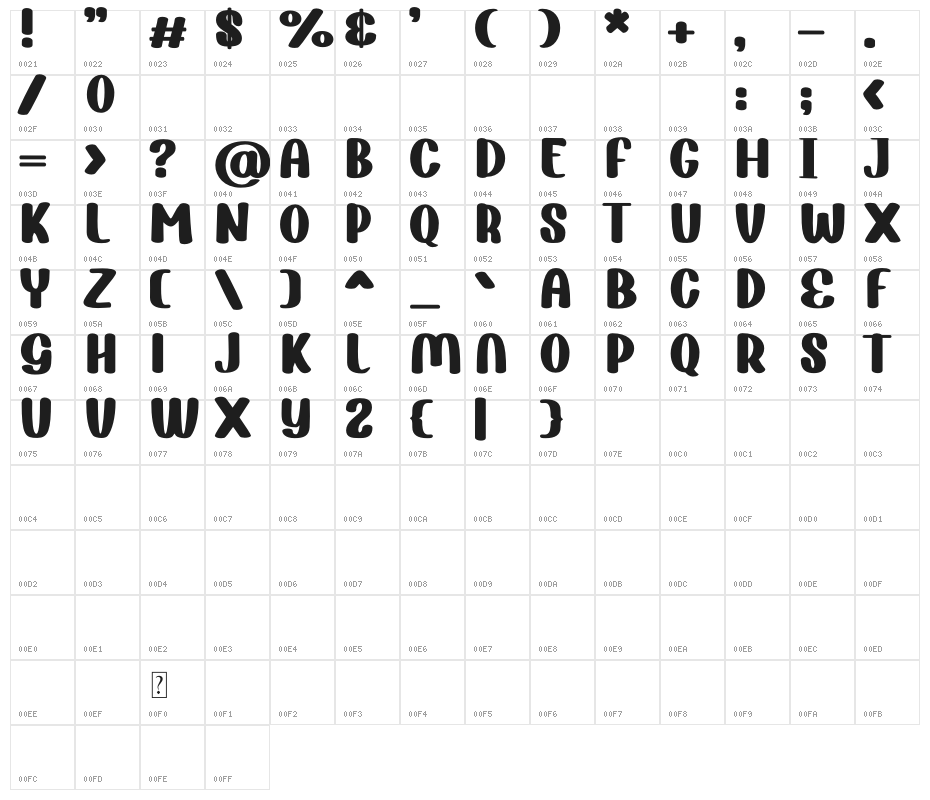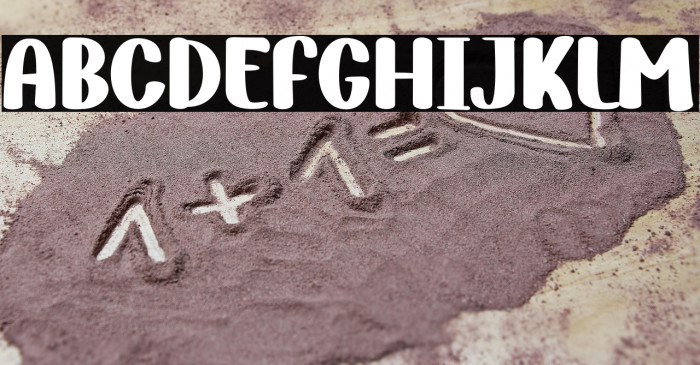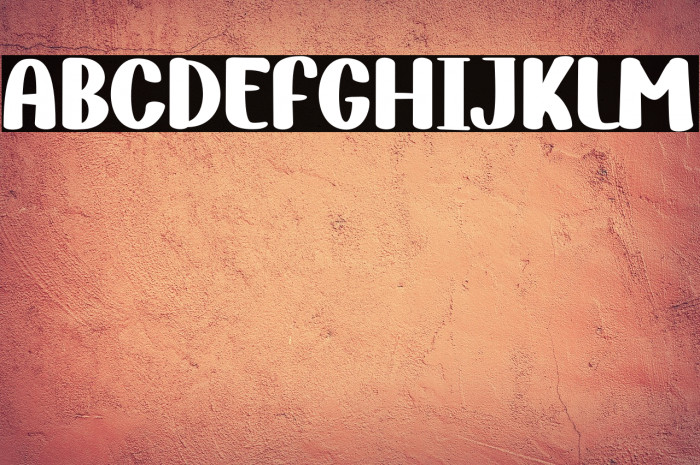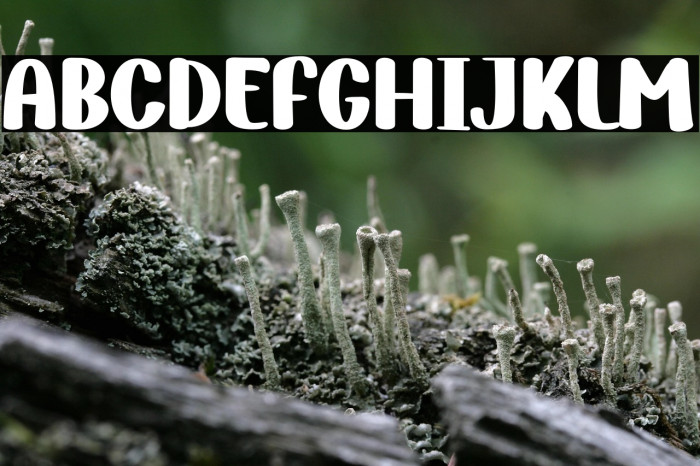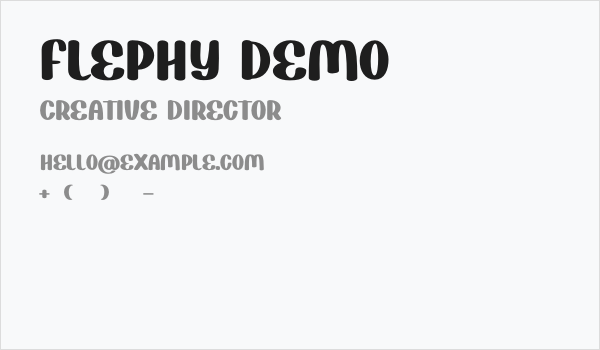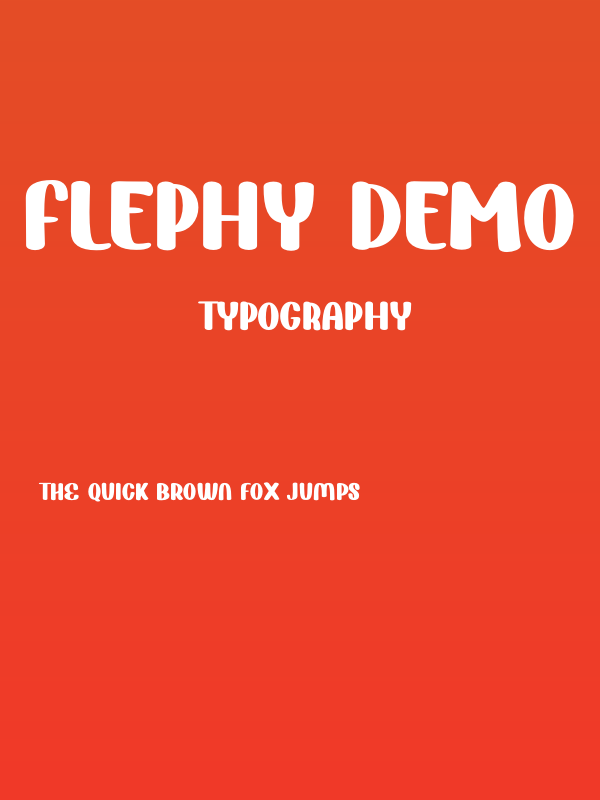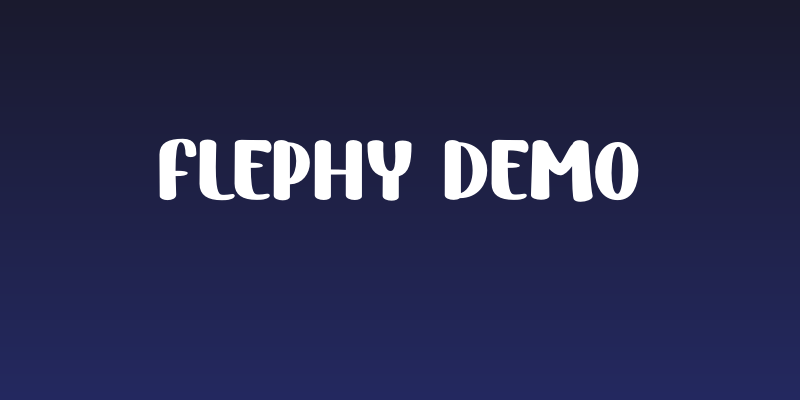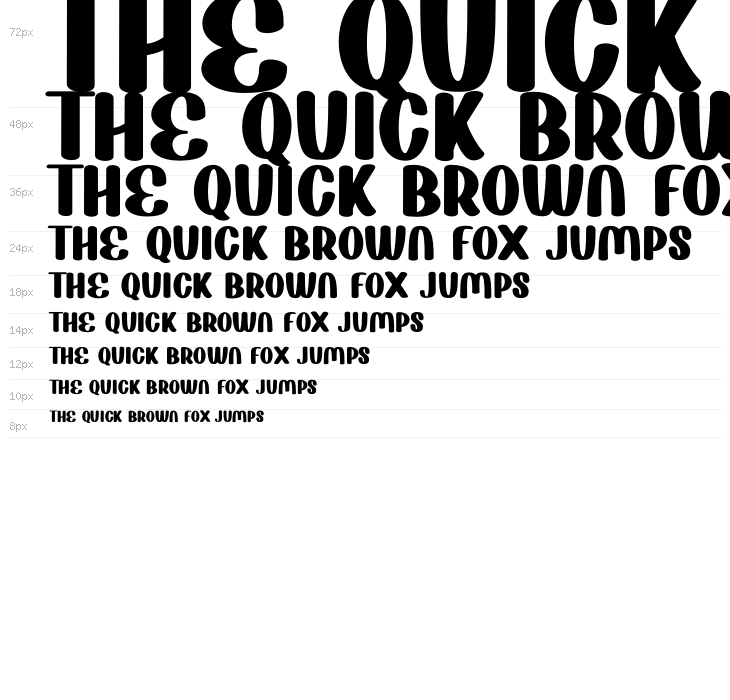
Flephy Demo Font
| Categorie | Cartoon |
| Stile generale | Playful, Whimsical |
| Caso d'uso | Headlines, Posters, Branding |
| Progetti proposti | Ideal for children's books, playful branding, event posters, and creative advertising. |